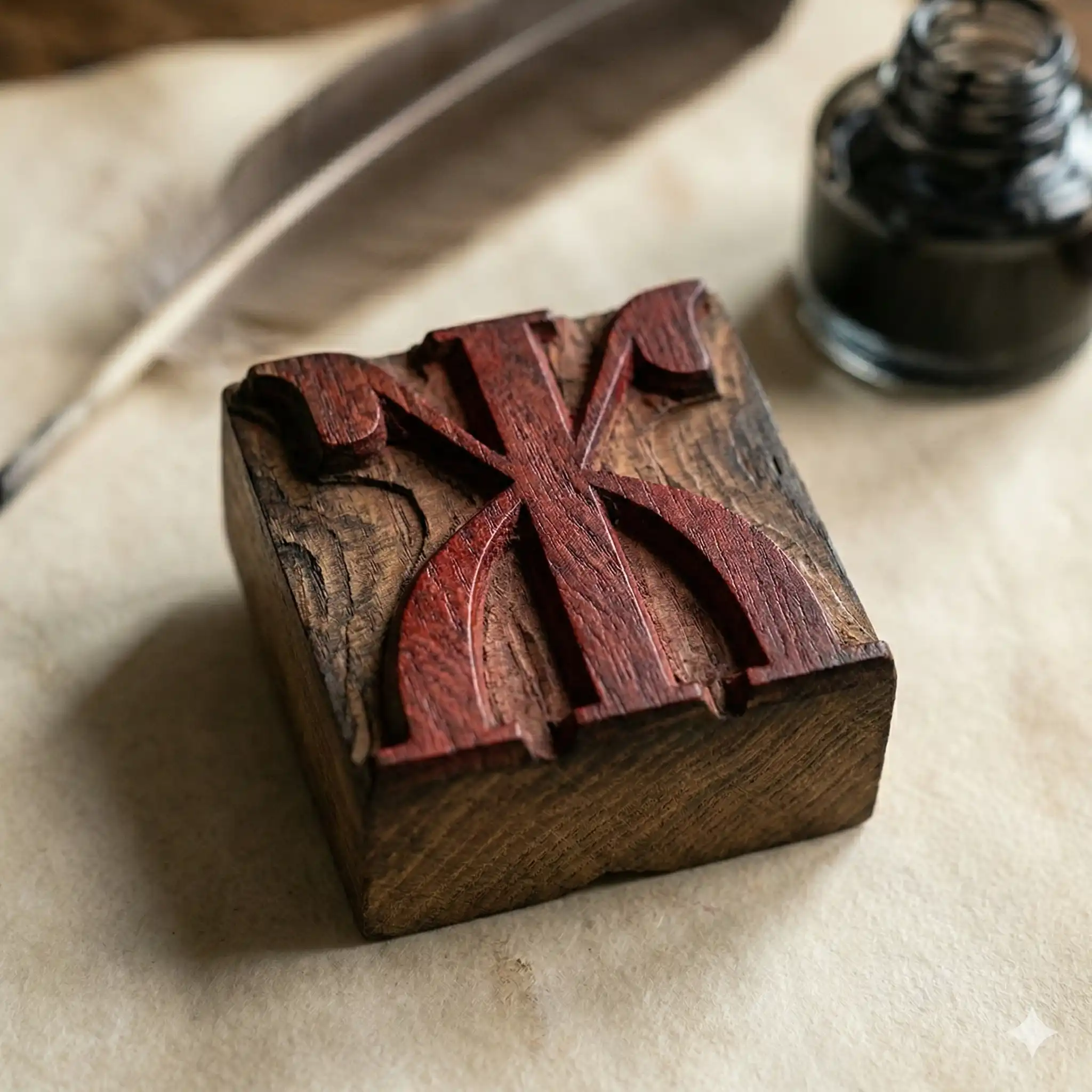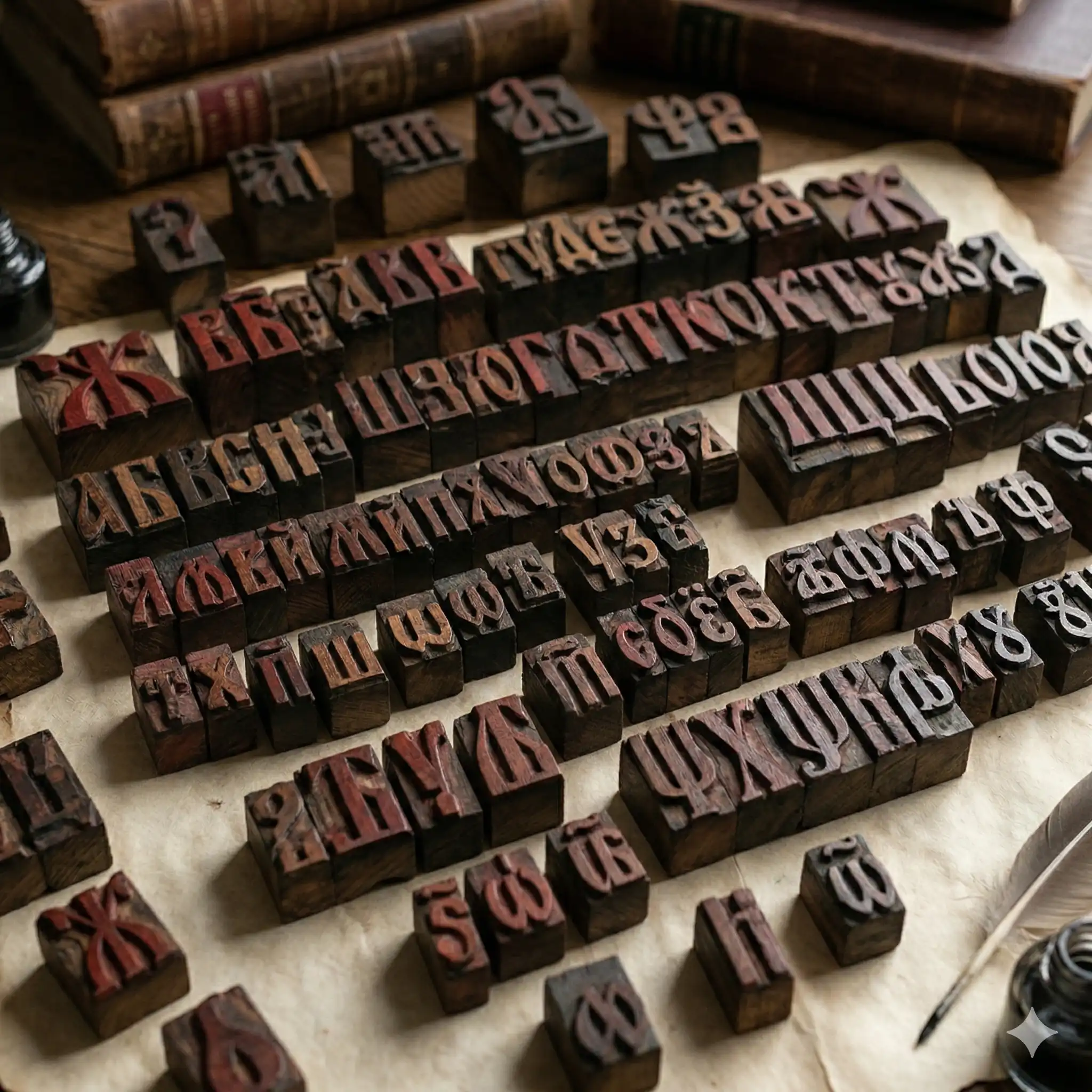
История, письменность и лингвистические особенности
Церковнославянский язык — славянский язык христианского богослужения и письменности, сформировавшийся из старославянского языка. Традиционный славянский язык богослужения, употребляемый Православной церковью в Болгарии, Сербии, Черногории, Северной Македонии, Польше, Белоруссии, на Украине и в России, а также отчасти в Молдавии, Словакии и Чехии (исторически также в Валахии). В большинстве церквей используется наряду с национальными языками.
Распространение церковнославянского языка в разных славянских странах сопровождалось его адаптацией к особенностям местных славянских языков. В результате уже с IX–X веков возникали территориальные разновидности языка — его изводы (варианты).
Наиболее распространённая форма из ныне употребляемых — современный синодальный извод церковнославянского языка, используемый как литургический язык Русской православной церковью и некоторыми другими религиозными объединениями. Кроме Русской православной церкви, церковнославянский язык — основной богослужебный язык славяно-византийского обряда Российской грекокатолической церкви, употребляется, наряду с украинским, в Украинской грекокатолической церкви, наряду с белорусским — в Белорусской грекокатолической церкви. До реформ 1960–1970-х годов, наряду с латинским, употреблялся в некоторых местах в Хорватии, в Католической церкви.
По аналогии с латынью, активно использующейся в медицине, биологии, юриспруденции, а также в Католической церкви, но не являющейся разговорным языком, церковнославянский язык также является мёртвым языком, используемым только в отдельной церковной книжно-письменной сфере, в гимнографии и ежедневном богослужении в некоторых православных и грекокатолических церквях.
Старославянская кириллица является основой письменности многих современных языков.
Название
Термин «церковнославянский язык» впервые появился в «Рассуждении о славянском языке» А. X. Востокова (1820) и указывает на преимущественно церковную сферу его использования. В филологических текстах древних славянских книжников и филологов Нового времени церковнославянский язык назывался «словенский», «славянщина». В филологической литературе до сих пор используется термин «славянизмы» в значении «церковнославянизмы». Поскольку церковнославянский язык развивался из старославянского и нет принципиальных различий между тем языком, который создали Кирилл и Мефодий, и тем, каким он становился в дальнейшем, в понятие «церковнославянский язык» нередко включается и старославянский язык.
История
Старославянский язык (ранняя форма церковнославянского) восходит к солунскому диалекту древнеболгарского языка, родному для создателей письменного старославянского языка Кирилла и Мефодия, хотя за время своего бытования он подвергся грамматическим и фонетическим упрощениям (в частности, исчезли носовые и редуцированные гласные) и сближению с живыми языками стран, в которых он бытует. Впервые был введён в культурный обиход в Великой Моравии.
В Моравии Кирилл и Мефодий вместе с учениками переводили церковные книги с греческого на старославянский язык, обучали славян чтению, письму и ведению богослужения на старославянском языке. В 869 году в Риме Кирилл умер, а Мефодий в следующем году вернулся в Моравию уже в звании архиепископа. После смерти Мефодия его преемником в Моравии стал его ученик Горазд Охридский.
При Горазде противники славянской письменности в Моравии добились у папы Стефана V запрещения славянского языка в церковной литургии, а ученики Мефодия были изгнаны из Моравии. Несмотря на это, распространение письменности на старославянском языке в Моравии и Чехии сразу не прекратилось. Известны литературные памятники, написанные в этих странах глаголицей на старославянском языке в X и XI веках — Киевские листки, Пражские отрывки и другие.
Ученики Мефодия, покинув Моравию, частично отправились к хорватам, а частично — в Болгарию, где продолжили дело развития славянской письменности. Именно Болгария и стала в конце IX века центром распространения письменности на старославянском языке. Здесь сформировались две крупных школы — Охридская и Преславская, в которых творили знаменитые болгарские книжники — Климент Охридский, Наум Охридский, Иоанн Экзарх, Константин Преславский и Черноризец Храбр.
В X веке, вместе с принятием христианства, старославянский в качестве литературного языка начинает использоваться в Древнерусском государстве, где образуется Древнерусский извод церковнославянского языка.
Первой печатной книгой на церковнославянском языке стал хорватский Ⰿⰹⱅⰰⰾⱏ ⱂⱁ ⰸⰰⰽⱁⱀⱆ ⱃⰹⰿⱅⰽⱁⰳⰰ ⰴⰲⱁⱃⰰ (Misal po zakonu rimskoga dvora), изданный в 1483 году глаголицей.
Письменность
Памятники старославянской и церковнославянской письменности известны как на глаголице, так и на кириллице.
На письме современный церковнославянский язык использует кириллицу. Церковнославянская азбука содержит около 40 букв, некоторые из которых представлены более чем одним вариантом написания (неопределённость с числом букв связана с неоднозначностью границы между разными буквами и разными вариантами одной буквы). Используются многочисленные надстрочные знаки (три вида ударения, придыхание, три сочетания придыхания с ударениями, ерок, кендема, краткая, простое титло, разнообразные буквенные титла). Знаки препинания несколько отличны от русских: так, вместо вопросительного знака используется точка с запятой, а вместо точки с запятой — двоеточие. Различаются прописные и строчные буквы, употребление которых может быть либо аналогичным русскому, либо следовать древней системе, в которой с большой буквы писалось преимущественно только первое слово абзаца.
| А а а҆́зъ | Б б бꙋ́ки | В в вѣ́ди | Г г глаго́ль | Д д добро̀ | Є є, е є҆́сть | Ж ж живѣ́те | Ѕ ѕ ѕѣлѡ̀ |
| З з землѧ̀ | И и и҆́же | І ї и҆̀ | К к ка́кѡ | Л л лю́дїє | М м мыслѣ́те | Н н на́шъ | Ѻ ѻ, о ѻ҆́нъ |
| Ѡ ѡ, Ѽ ѽ ѡ҆ме́га | П п поко́й | Р р рцы̀ | С с сло́во | Т т тве́рдо | Ѹ ѹ, Ꙋ ꙋ ѹ҆́къ | Ф ф фе́ртъ | Х х хѣ́ръ |
| Ѿ ѿ ѡ҆́тъ | Ц ц цы̀ | Ч ч че́рвь | Ш ш ша̀ | Щ щ ща̀ (шта̀) | Ъ ъ є҆́ръ | Ы ы є҆ры̀ | Ь ь є҆́рь |
| Ѣ ѣ ꙗ҆́ть | Ю ю ю҆̀ | Ꙗ ꙗ ꙗ҆̀ | Ѧ ѧ ю҆́съ ма́лый | Ѯ ѯ ксѝ | Ѱ ѱ псѝ | Ѳ ѳ ѳита̀ | Ѵ ѵ ѵ҆́жица |
Типографика
Церковнославянский текст традиционно печатается шрифтами одного и того же рисунка, восходящего к строгому русскому полууставу XVI века. Соответствия жирному и курсивному шрифтам нет. Для выделений используется набор вразрядку, набор одними прописными буквами, набор более мелким или более крупным шрифтом. В богослужебных книгах применяется печать в две краски: например, красным печатаются заголовки и указания для читающего, а чёрным — то, что надо произносить вслух.
Ещё до революции некоторые церковнославянские тексты для мирян (например, молитвословы) печатались гражданским шрифтом, чаще всего с обозначением ударения во всех многосложных словах. Их появление было связано с тем, что стали утрачиваться навыки чтения церковнославянского текста в стандартной записи. После революции в СССР и за рубежом стали выходить и богослужебные книги (например, минеи, ирмологии) с использованием русской современной (в СССР) или дореволюционной (чаще всего за рубежом) орфографии с ударениями. Причиной было отсутствие церковнославянских типографских шрифтов, которые в Советском Союзе были физически уничтожены.
Влияние на другие языки
Церковнославянский язык оказал большое влияние на многие литературные славянские языки, особенно народов православной культуры. Многочисленные заимствования церковнославянских слов породили в русском языке своеобразное явление — фонетически выраженную стилевую разницу в парах слов одного и того же корня, например: золото — злато, город — град, рожать — рождать (первое слово каждой пары русское, второе заимствовано из церковнославянского). В образовавшихся таким образом синонимических парах церковнославянское заимствование обычно относится к более высокому стилю. В ряде случаев русский и церковнославянский варианты одного и того же слова разошлись (полностью или частично) в семантике и уже не являются синонимами: горячий — горящий, ровный — равный, сбор — собор, порох — прах, совершённый — совершенный, падёж — падеж, нёбо — небо.
Лингвистическая характеристика
Фонетика и фонология
Характеристики произношения церковнославянского языка:
- отсутствует редукция гласных в безударных слогах. Например, «о» и «е» в безударном положении читаются как [о] и [е] (как в северных окающих диалектах), в то время как в русском литературном произношении они превращаются в [а], [ʌ] или [ъ] и в [и] или [ь] соответственно;
- буква «е» никогда не читается как ё (собственно, в церковнославянском письме буквы ё нет вообще), что отражено и в заимствованиях из церковнославянского в русский: небо — нёбо, одежда — одёжа, надежда — надёжа (первое слово каждой пары заимствовано из церковнославянского, второе — исконно русское);
- буква «г» читалась как звонкий фрикативный согласный [ɣ] (как в южнорусских диалектах или приблизительно как в украинском языке), а не как смычный [ɡ] в русском литературном произношении; в позиции оглушения [ɣ] превращается в [x] (это повлияло на русское произношение слова Бог как [Бох]). В настоящее время в языке богослужения фрикативное произношение можно услышать как в патриаршей церкви, так и у старообрядцев.
- окончания прилагательных «-аго» («-ѧго») и местоимений «-ого» («-его») (с омегой в родительном падеже, с буквой «о» — в винительном) произносятся как пишутся, в то время как в русском -ого произносится как [-ʌво́] — в ударной позиции и как [-ъвъ] — в безударной.
- если приставка оканчивается на твёрдый согласный, а корень начинается с «и», например: ѿиметъ (‘отымет’), то «и» читается как [ы].
- буквы «ш», «ж», «щ», «ч», «ц» произносятся как в русском и, так же как в русском, после них пишется только «ꙋ» и почти никогда «ю», хотя все эти согласные этимологически мягкие.
Впрочем, церковнославянская письменность не вполне фонетична: так, после шипящих смена букв «и» — «ы» и «а» — «ѧ» на произношение не влияет и служит лишь для того, чтобы избежать омонимии; использование мягкого знака между согласными («тма» — «тьма» и т. п.) в ряде случаев факультативно (в русском произношении тут смягчение возможно, а сербские церковнославянские буквари пишут, что «ь» тут ничего не обозначает и пишется только по традиции). Вообще, в церковнославянском произношении допускается более или менее сильный акцент местного языка (русского, украинского, болгарского, сербского и т. п.). В современном русском церковнославянском произношении употребляется даже аканье, хотя ещё в начале XX века оно никогда не употреблялось и считается неверным до сих пор.
Морфология
Церковнославянский язык, как и русский, является преимущественно синтетическим. Это означает, что грамматические категории выражаются преимущественно словоизменением (склонение, спряжение), а не служебными словами.
Имя существительное
В церковнославянском языке насчитывается 7 падежей:
- именительный,
- винительный,
- родительный,
- дательный,
- творительный,
- местный,
- звательный.
Падежные значения выражаются окончаниями и предложно-падежными конструкциями, а также согласованием в падеже атрибутивных частей речи.
Глагол
У церковнославянского глагола выделяют категории наклонения, времени, лица, числа и залога (у именных форм глагола также рода). Всего у глагола насчитывается 6 времён: плюсквамперфект, имперфект, аорист (I и II), настоящее и будущее. Ниже приводятся таблицы спряжения глагола «бы́ти».
| Лицо | Ед. ч. | Дв. ч. | Мн. ч. | |
|---|---|---|---|---|
| м. р. | ж., ср. р. | |||
| 1‑е | (а҆́зъ) є҆́смь | (мы̀) є҆сва̀, ‑ма̀ | є҆свѣ̀, ‑мѣ̀ | є҆смы̀ |
| 2‑е | (ты̀) є҆сѝ | (вы̀) є҆ста̀ | є҆стѣ̀ | є҆стѐ |
| 3‑е | (ѻ҆́нъ, ‑а̀, ‑о̀) є҆́сть | (ѻ҆нѝ) є҆ста̀ | є҆стѣ̀ | сꙋ́ть |
| Лицо | Ед. ч. | Дв. ч. | Мн. ч. | |
|---|---|---|---|---|
| м. р. | ж., ср. р. | |||
| 1‑е | (а҆́зъ) нѣ́смь | (мы̀) нѣ́сва, ‑ма | нѣ́свѣ, ‑мѣ | нѣ́смы |
| 2‑е | (ты̀) нѣ́си | (вы̀) нѣ́ста | нѣ́стѣ | нѣ́сте |
| 3‑е | (ѻ҆́нъ, ‑а̀, ‑о̀) нѣ́сть | (ѻ҆нѝ) нѣ́ста | нѣ́стѣ | не сꙋ́ть |
| Лицо | Ед. ч. | Дв. ч. | Мн. ч. | |
|---|---|---|---|---|
| м. р. | ж., ср. р. | |||
| 1‑е | (а҆́зъ) бꙋ́дꙋ | (мы̀) бꙋ́дева | бꙋ́девѣ | бꙋ́демъ |
| 2‑е | (ты̀) бꙋ́деши | (вы̀) бꙋ́дета | бꙋ́детѣ | бꙋ́дете |
| 3‑е | (ѻ҆́нъ, ‑а̀, ‑о̀) бꙋ́детъ | (ѻ҆нѝ) бꙋ́дета | бꙋ́детѣ | бꙋ́дꙋтъ |
| Лицо | Ед. ч. | Дв. ч. | Мн. ч. | |
|---|---|---|---|---|
| м. р. | ж., ср. р. | |||
| 1‑е | (а҆́зъ) бы́хъ | (мы̀) бы́хова | бы́ховѣ | бы́хомъ |
| 2‑е | (ты̀) бы̀ | (вы̀) бы́ста | бы́стѣ | бы́сте |
| 3‑е | (ѻ҆́нъ, ‑а̀, ‑о̀) бы́сть (бы̀) | (ѻ҆нѝ) бы́ста | бы́стѣ | бы́ша |
| Лицо | Ед. ч. | Дв. ч. | Мн. ч. | |
|---|---|---|---|---|
| м. р. | ж., ср. р. | |||
| 1‑е | (а҆́зъ) бѣ́хъ | (мы̀) бѣ́хова | бѣ́ховѣ | бѣ́хомъ |
| 2‑е | (ты̀) бѣ̀ | (вы̀) бѣ́ста | бѣ́стѣ | бѣ́сте |
| 3‑е | (ѻ҆́нъ, ‑а̀, ‑о̀) бѣ̀ | (ѻ҆нѝ) бѣ́ста | бѣ́стѣ | бѣ́ша |
| Лицо | Ед. ч. | Дв. ч. | Мн. ч. | |
|---|---|---|---|---|
| м. р. | ж., ср. р. | |||
| 1‑е | (а҆́зъ) бѧ́хъ | (мы̀) бѧ́хова | бѧ́ховѣ | бѧ́хомъ |
| 2‑е | (ты̀) бѧ́ше | (вы̀) бѧ́ста | бѧ́стѣ | бѧ́сте |
| 3‑е | (ѻ҆́нъ, ‑а̀, ‑о̀) бѧ́ше | (ѻ҆нѝ) бѧ́ста | бѧ́стѣ | бѧ́хꙋ (бѣ́хꙋ) |
Отрицательная форма глагола «бы́ти» в настоящем времени образуется путём слияния частицы «не» и глагольной формы в одно слово: «не» + «є҆́смь» = «нѣ́смь», «не» + «є҆сѝ» = «нѣ́си», «не» + «є҆́сть» = «нѣ́сть» и т. д., за исключением формы 3‑го л. мн. ч. — «не сꙋ́ть». Инфинитив образуется с помощью суффикса «-ти»: «ѡ҆брѣ́зати» (‘обре́зать’), «написа́ти» (‘написа́ть’). Аорист 1‑го лица единственного числа образуется с помощью окончания «‑хъ»: «А҆́зъ писа́хъ» (‘Я написа́л’); «А҆́зъ ѹ҆снꙋ́хъ, и҆ спа́хъ, воста́хъ». Также в прошлом времени 3‑го лица множественного числа есть окончание «‑ша»: «Ѻ҆нѝ прїидо́ша, слы́шаша, положи́ша» (‘Они пришли, услышали, положили’). Перфект образуется с помощью окончания «‑лъ» и глагола «бы́ти» в настоящем времени: «ѡ҆брѣла̀ є҆́сть» (‘[она] обрела’). Плюсквамперфект образуется с помощью окончания «-лъ» и глагола «бы́ти» в аористе (от основы на «‑бѣ») или имперфекте: «Ѻ҆нѝ ѿшлѝ бѧ́хꙋ» (‘Они было отошли’).
Запись цифр и чисел
В церковнославянском языке для записи цифр используют кириллическую систему, или цифирь. Она отчасти подобна римской: для записи чисел используются буквы алфавита, имеющие цифровые значения. Для обозначения числа используют знак титла (҃).
Буквы, имеющие цифровое значение, представлены в таблице.
| Цифры | Числа | ||||
|---|---|---|---|---|---|
| цифири | арабские | цифири | арабские |
| а҃ | 1 | і҃ | 10 | р҃ | 100 |
| в҃ | 2 | к҃ | 20 | с҃ | 200 |
| г҃ | 3 | л҃ | 30 | т҃ | 300 |
| д҃ | 4 | м҃ | 40 | у҃ | 400 |
| є҃ | 5 | н҃ | 50 | ф҃ | 500 |
| ѕ҃ | 6 | ѯ҃ | 60 | х҃ | 600 |
| з҃ | 7 | ѻ҃ | 70 | ѱ҃ | 700 |
| и҃ | 8 | п҃ | 80 | ѿ҃ | 800 |
| ѳ҃ | 9 | ч҃ | 90 | ц҃ | 900 |
Числа, не указанные выше, получаются путём соединения букв. Для получения чисел от 11 до 19 сначала ставится младший разряд, затем старший, например: а҃і — 11, є҃і — 15, ѕ҃і — 16; для чисел от 21 и далее — наоборот, запись ведётся от старшего разряда к младшему, например: к҃д — 24, ѻ҃в — 72, ун҃г — 453.
Тысяча обозначается знаком ҂, опущенным под строку. Числовое значение буквы, стоящей за этим знаком, увеличивается в 1000 раз, например: ҂а҃ — 1000, ҂вє҃і — 2015, ҂і҂єл҃г — 15 033.
Для облегчения записи более крупных чисел на усмотрение автора используются следующие символы: а⃝ — тьма, означает 10 000-кратное увеличение значения обведённой буквы, например: а⃝ — 10 000; а҈ — легион, означает 100 000-кратное увеличение значения обведённой буквы, например: г҈ — 300 000; а҉ — леодр, означает 1 000 000-кратное увеличение обведённой буквы, например: в҉ — 2 000 000, — и другие.
Таким образом, в записи более крупных чисел есть варианты: так, например, число 5 913 769 может быть записано либо как ҂҂є҂ц҂і҂гѱѯ҃ѳ, либо как є҉ ѳ҈ а⃝ ҂гѱѯ҃ѳ.
Синтаксис
Как и в русском языке, простое предложение чаще всего состоит из подлежащего и сказуемого, причём подлежащее стоит в именительном падеже. Сказуемое же может быть выражено глаголом, именной частью речи или именной частью речи со вспомогательным глаголом.
В области синтаксиса заметно греческое влияние в употреблении ряда конструкций:
- именительный падеж в качестве приложения при звательном падеже;
- родительный падеж с предлогом, обозначающий агенс в пассивной конструкции;
- множественное число среднего рода слов-определений в функции субстантивированного обобщения;
- винительный падеж с инфинитивом при глаголах речи, чувств.
Много общего в синтаксисе причастий греческого и церковнославянского языков: большей частью эти схождения опирались на явления живого славянского языка; греческое влияние способствовало распространению некоторых конструкций (глагол «бы́ти» с причастием, причастия после фазовых глаголов и др.), привело к сравнительно частому употреблению самостоятельного дательного падежа на месте греческого самостоятельного родительного падежа; в отдельных случаях фиксируется и калькирование греческих причастных конструкций, но оно не закрепилось и осталось в рамках отдельного употребления, а не системы языка.